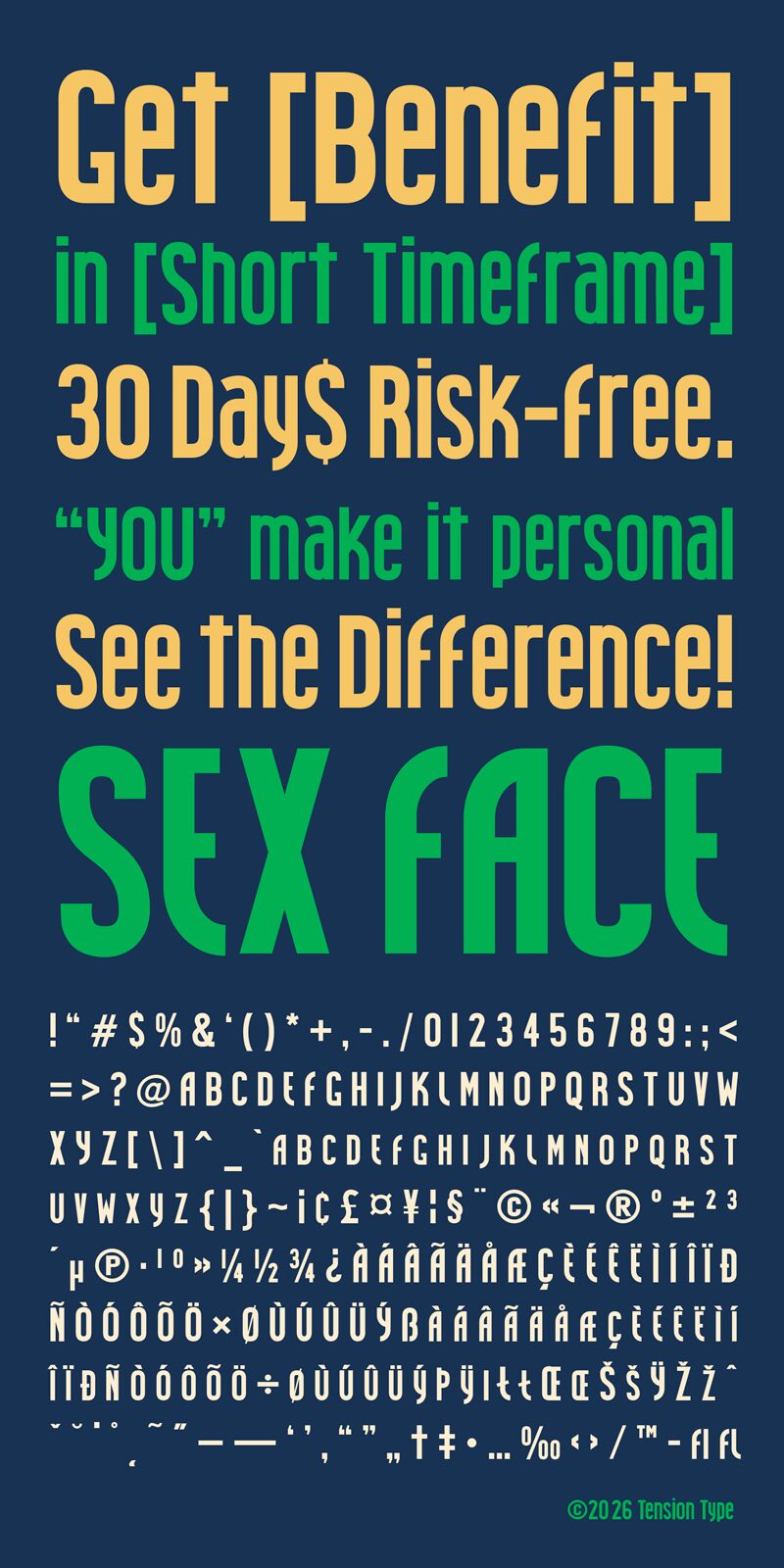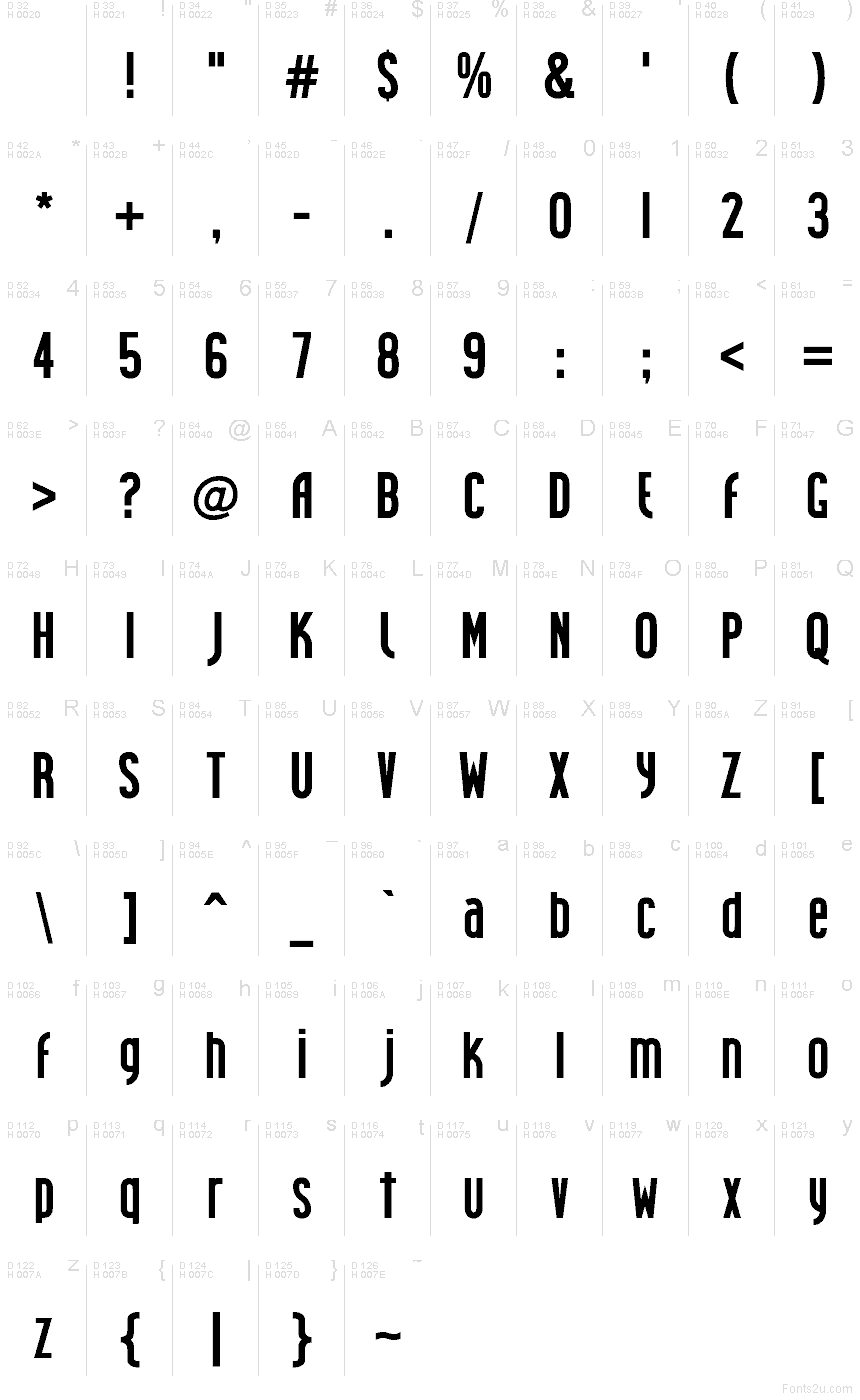
Sex Face
Sex Face es una tipografía sans serif gratuita con una forma alta y condensada y esquinas redondeadas que le dan a las letras un ritmo fluido y compacto. Las formas se ven estrechas y verticales, con trazos uniformes y curvas suaves que mantienen el diseño compacto sin parecer rígido.
Sex Face funciona muy bien para portadas de álbumes, titulares de pósteres, gráficos para redes sociales, etiquetas de moda y logotipos cortos donde esa estructura comprimida permite que la línea de texto destaque con fuerza. Esta fuente gratuita también es adecuada para folletos de eventos y detalles editoriales, especialmente cuando buscas una sans serif sencilla que mantenga su forma en frases cortas de gran impacto.
Mi segundo diseño de tipografía sans serif. Me encantan las letras condensadas, así que eso fue lo que hice. Es genial para titulares, pósteres, logotipos o cualquier uso en tamaño grande. No es ideal para texto principal :)
My second design of a sans serif font. I like condensed type a lot, so that’s what I did. A big learning curve!